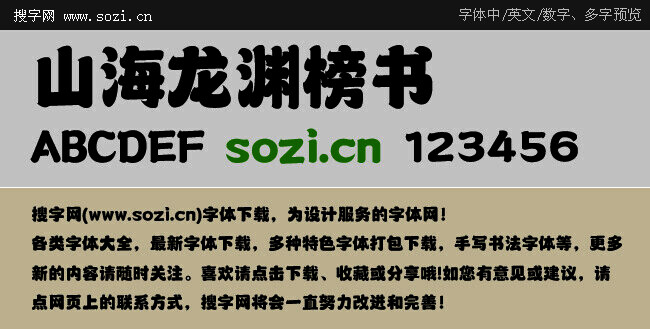
山海龍淵榜書(shū)
搜字網(wǎng)提供一款山海龍淵榜書(shū)中文書(shū)法字體下載,該字體雄健有力,霸氣外露,在粗細(xì)的縱橫間,擁有非常規(guī)的張力特性。該字體的筆畫(huà)充滿力量感,組合搭配極富強(qiáng)烈的節(jié)奏感,融入楷書(shū)特點(diǎn),使字體的視覺(jué)效果有力、寬厚、方正,充滿了穩(wěn)重感和設(shè)計(jì)感。適合標(biāo)題設(shè)計(jì)、包裝設(shè)計(jì)、海報(bào)設(shè)計(jì)、廣告設(shè)計(jì)等應(yīng)用。